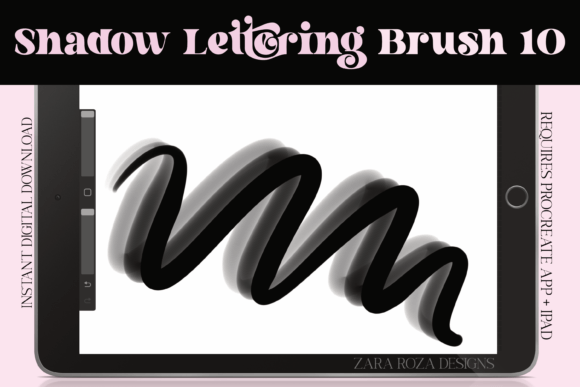
Procreate Shadow Lettering Brush 10
✨ Procreate Shadow Lettering Brush 10 : Le Secret des Lettrages Vintage qui Sublime Vos Illustrations ✨
Vous rêvez de donner à vos créations digitales une touche rétro, authentique et pleine de caractère ? Le Procreate Shadow Lettering Brush 10 est la brosse ultime pour les artistes qui veulent transformer leurs lettrages en véritables œuvres d’art. Que vous soyez illustrateur, fan de manga, créateur de chibi, ou simply passionné de calligraphie digitale, cette brosse est conçue pour vous.
📌 Pourquoi Ce Brush Est-Il Une Révolution ?
Conçu avec une attention maniaque aux détails, le Shadow Lettering Brush 10 imite à la perfection l’effet d’un stylo-liner ou d’un marqueur vintage, avec une ombre subtile et dynamique qui donne du volume et de la profondeur à chaque trait. Pas besoin de calques, pas besoin d’effets supplémentaires : l’ombre est intégrée directement dans le balayage de votre Apple Pencil.
- ✅ Esthétique rétro-vintage : Parfait pour les comics, les dessins animés et les œuvres inspirées des années 70-90
- ✅ Contrôle précis : Réagit comme un vrai stylo à encre — idéal pour les lignes fines, les détails et les contours énergiques
- ✅ Multi-usages : Lettrage, calligraphie, dessins de mode, portraits cartoon, manga, anime, doodles, sketching et bien plus encore
- ✅ Optimisé pour Apple Pencil : Sensibilité à la pression et au tilt pour une expérience fluide et naturelle
- ✅ 1 seule brosse, 1000 possibilités : Du lettrage élégant aux traits grossiers de bande dessinée, tout est possible
Procreate Shadow Lettering Brush 10 n’est pas juste une brosse — c’est une clé pour libérer votre style artistique. Que vous soyez débutant ou professionnel, ce brush vous permet de passer du simple trait à l’œuvre d’art en quelques secondes.